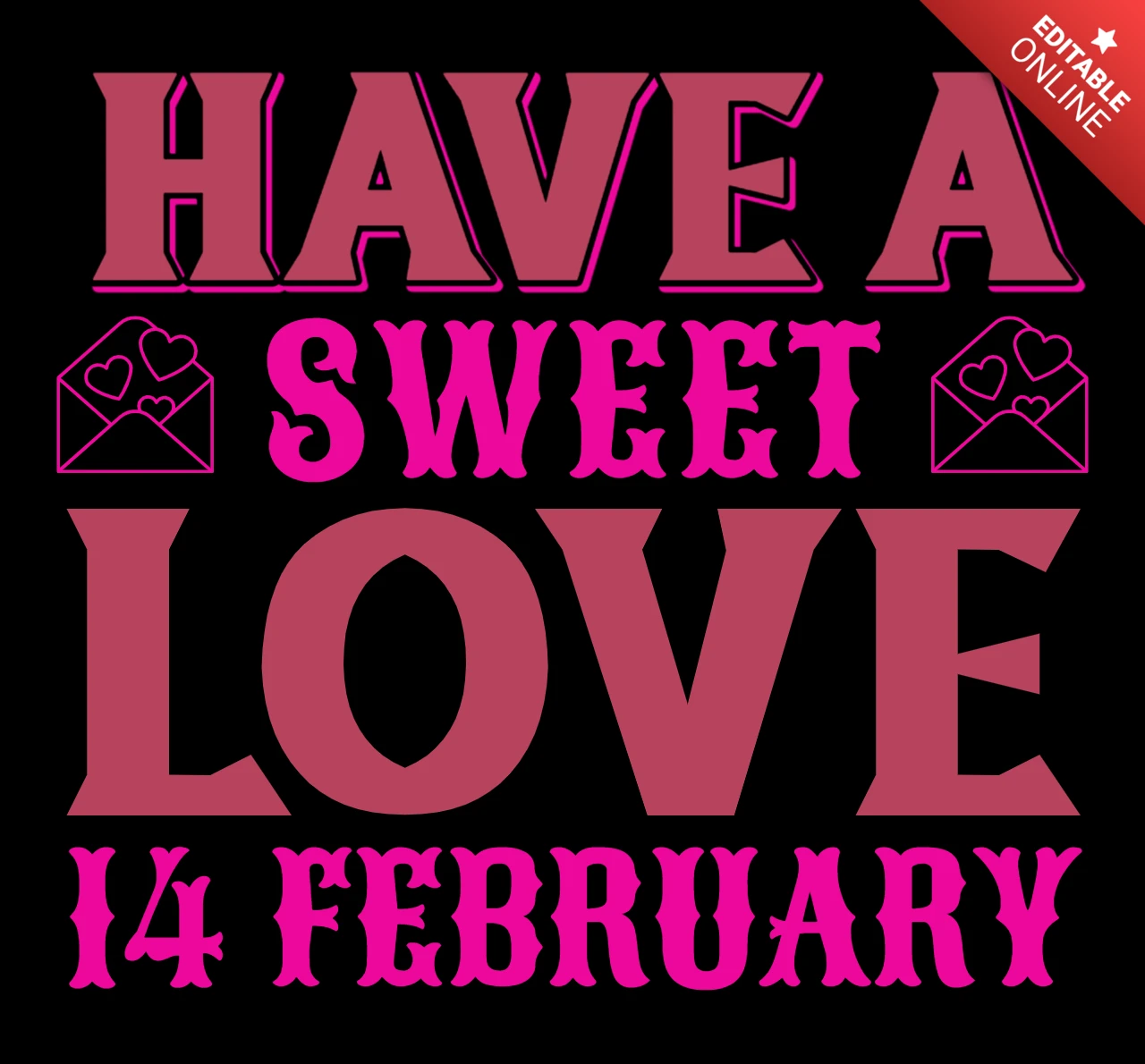
Modèle pour la Saint-Valentin avec typographie rétro audacieuse
Éditer dans Design Studio Télécharger en JPGCréez un t-shirt rétro et audacieux pour la Saint-Valentin grâce à notre modèle de conception coloré, doté d'une typographie expressive et d'illustrations ludiques qui font une déclaration sincère en faveur de l'amour et du rire.